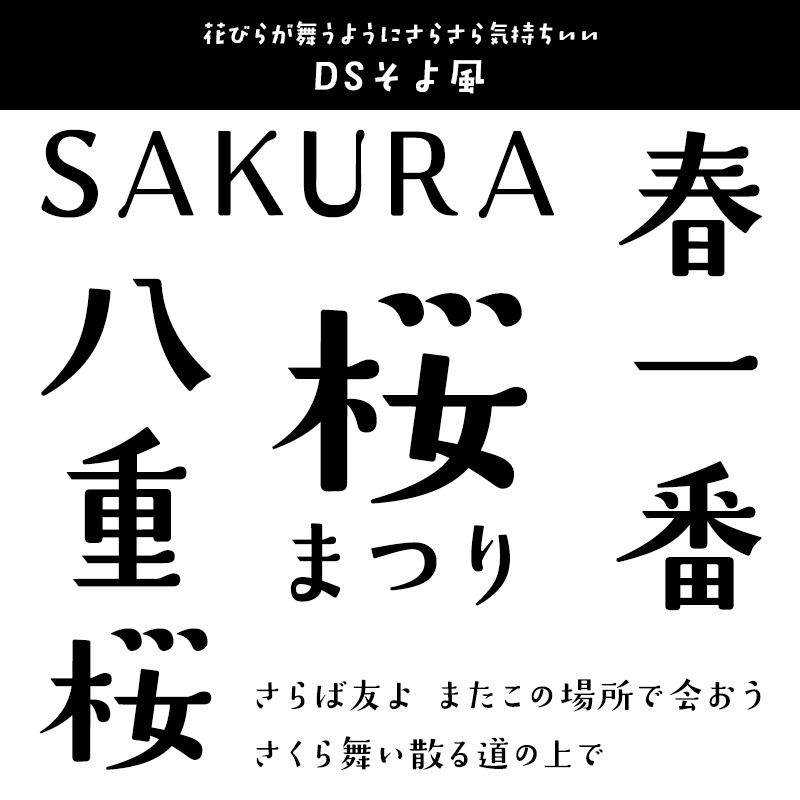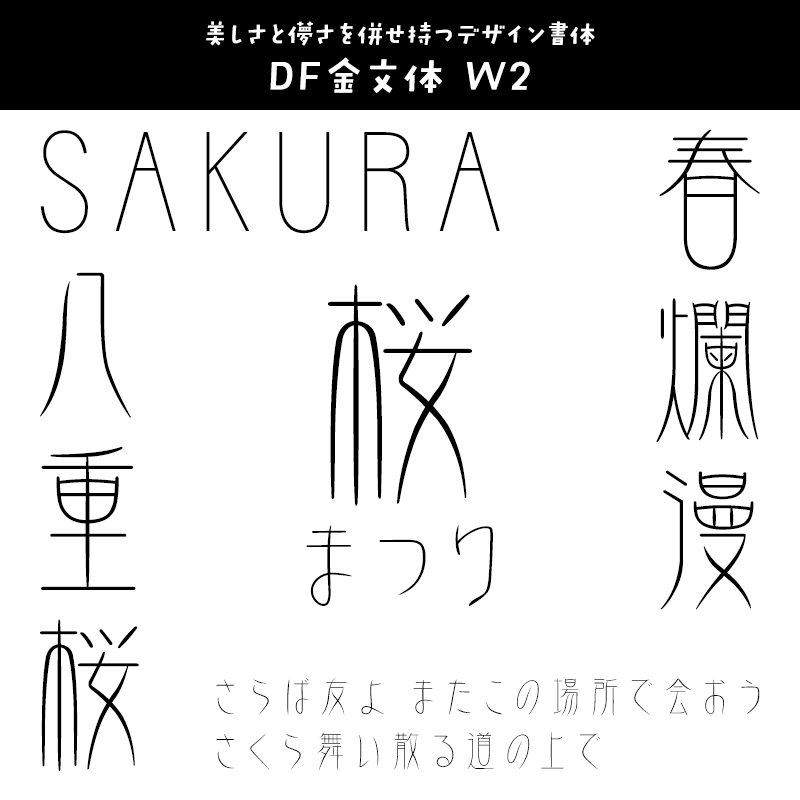
「さくら」に合うフォント:特化型 目的別フォントガイド #087
今回は「さくら」に合うフォント。日々フォントのことばかり考えている当店スタッフが直感的に選んだフォントをご紹介します。
「さくら」に合うフォントをスタッフが選びました
「さくら」に合うフォント TMミモザStdN
ペンのにじみを残した手書き文字
TMミモザStdN【タンデムフォント】
「さくら」に合うフォント TMミモザStdN
ペンのにじみを残した手書き文字。穏やかで美しい桜のイメージにぴったりな、ナチュラル感のあるフォントです。
「さくら」に合うフォント 空とひこうき
ノスタルジーを感じる等身大の手書き文字
空とひこうき【鈴木メモ】
「さくら」に合うフォント 空とひこうき
卒業アルバムの寄せ書きのような、パリパリのYシャツのような。青春の1ページにぴったりな手書きの温かみを感じる鈴木メモの手書きフォントです。
「さくら」に合うフォント F1-手紙
便箋はやっぱり桜模様で合わせたい
F1-手紙【FONT1000】
「さくら」に合うフォント F1-手紙
大切な人に書いた手紙のような、優しい筆致の手書き文字は、デザインにアクセントが欲しい時、そっと忍ばせたい書体です。
「さくら」に合うフォント 桜花
桜の花びらのような太い一画が特徴的な毛筆フォント
桜花【白舟書体】
「さくら」に合うフォント 桜花
『桜花』は、正統的な行書ではないものの、流れるような極細の線が美しい書体。1文字に1つある太い一画は花びらを象徴しています。
「さくら」に合うフォント 丸明Shinano
桜のような和の情緒あふれる明朝体
丸明Shinano【砧書体制作所】
「さくら」に合うフォント 丸明Shinano
ゴシックに丸ゴシックがあるように、明朝体にも丸明朝体というカテゴリーがあることを実証した書体。縦線、横線、点、トメ、ハライなどどれも先端が丸く処理されています。桜のような和の情緒あふれる、味のある明朝体です。
「さくら」に合うフォント DSそよ風
花びらが舞うようにさらさら気持ちいい
DSそよ風【七種泰史/デザインシグナル】
「さくら」に合うフォント DSそよ風
風に吹かれる桜の花びらのように軽やかな明朝タイプのデザインフォントです。同時発売の「なみ風」とのお得なセット商品もご用意しています。
「さくら」に合うフォント KOきざはし金陵M
美しい桜の風景に馴染む美しい漢字
KOきざはし金陵M【欣喜堂】
「さくら」に合うフォント KOきざはし金陵M
和字書体きざはしMに漢字と欧文を追加した総合書体です。流れるような筆致が美しい漢字は伝統的な日本の風景に馴染むので、季節問わず大活躍します。
「さくら」に合うフォント イワタ福まるごウネルL
柔らかい仮名がほっこりします
イワタ福まるごウネルL【イワタ】
「さくら」に合うフォント イワタ福まるごウネルL
右上がりで華やかな曲線が特徴的な丸ゴシック体。見ているだけで癒されるデザインで、桜の隣に添えたいフォントです。
「さくら」に合うフォント イワタ福まるごアソブ L
端正なフォルムが美しい丸ゴシック体
イワタ福まるごアソブ L【イワタ】
「さくら」に合うフォント イワタ福まるごアソブ L
カジュアルさの中に軽快なリズムを持たせた書体で、親しみやすい遊び心に、ノスタルジックな面持ちも備えています。
「さくら」に合うフォント DF金文体
美しさと儚さを併せ持つデザイン書体
DF金文体【ダイナフォント】
「さくら」に合うフォント DF金文体
殷、周、秦時代に青銅器に鋳込み刻まれた文字「金文」をモチーフにした書体です。高級感もあり、作品の印象を変えてくれます。
「さくら」に合うフォント モトヤアネモネ1
儚くも凛々しい美しい書体
モトヤアネモネ1【モトヤ】
「さくら」に合うフォント モトヤアネモネ1
情緒たっぷりの淡いイメージが桜にピッタリ。見方を変えれば幅広いデザインに重宝する細字フォントです。
「さくら」に合うフォント TA-桜
桜のイメージに合う優しい雰囲気の手書き風書体
TA-桜【FONT1000】
「さくら」に合うフォント TA-桜
優しい雰囲気を持った手書き風フォント。素朴で可愛らしいフォルムが桜っぽい。
「さくら」に合うフォント Aloha
スッキリ軽やか絵になるフォント
Aloha【絵になるフォント】
「さくら」に合うフォント Aloha
多数のイラスト(絵文字)が収録された変わり種フォントではありますが、文字自体のスッキリしたデザインは柔らかくもあり正に絵になるフォントです。